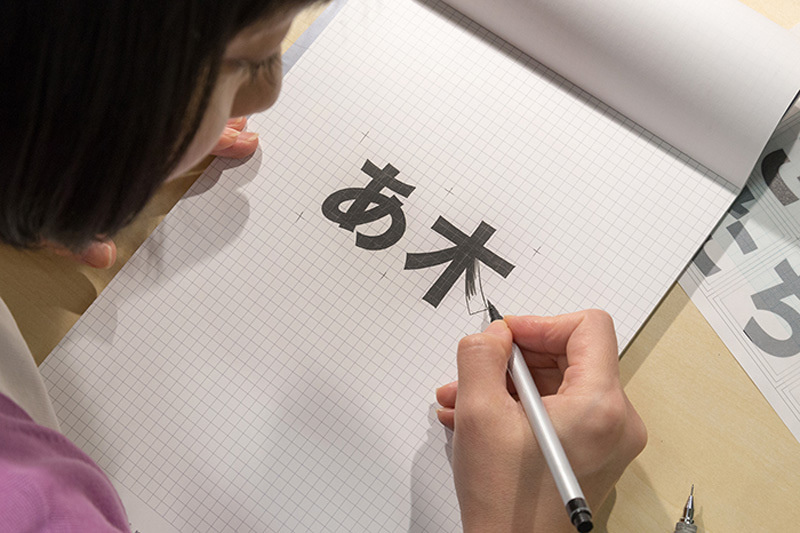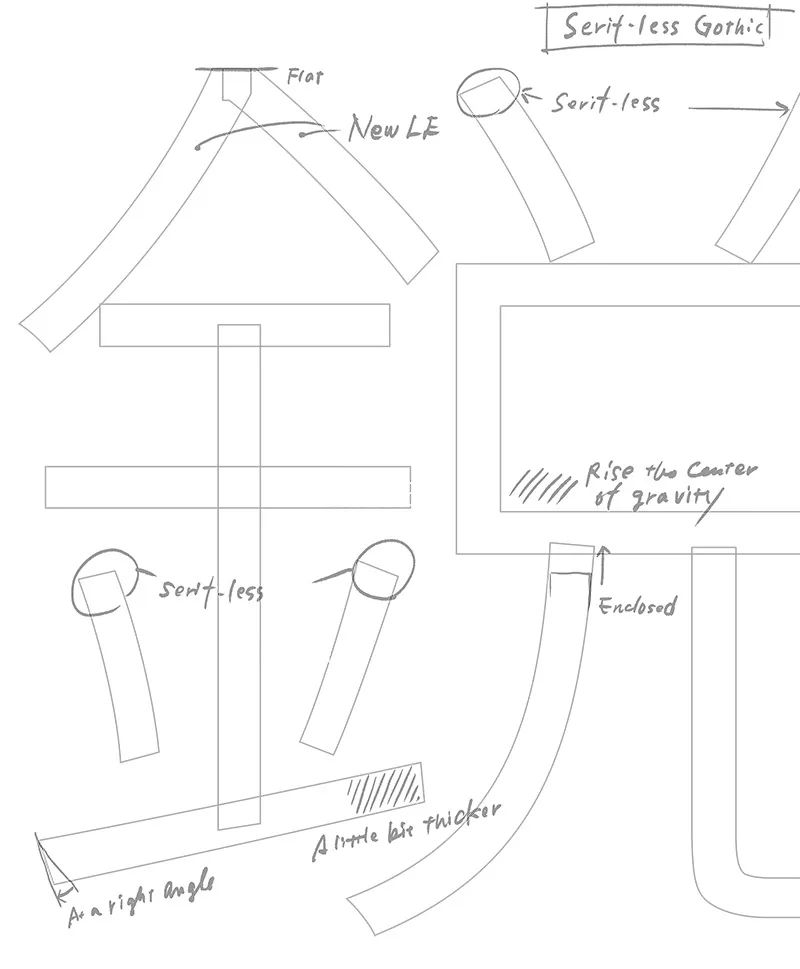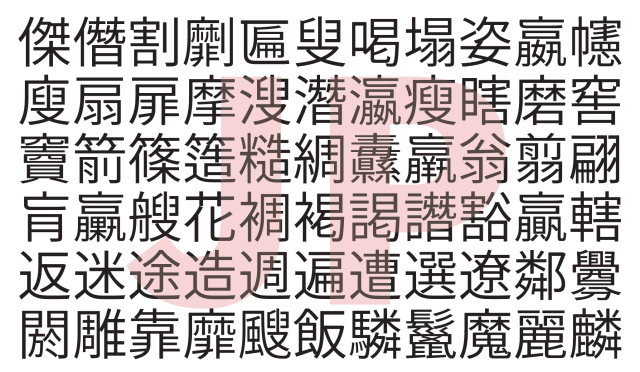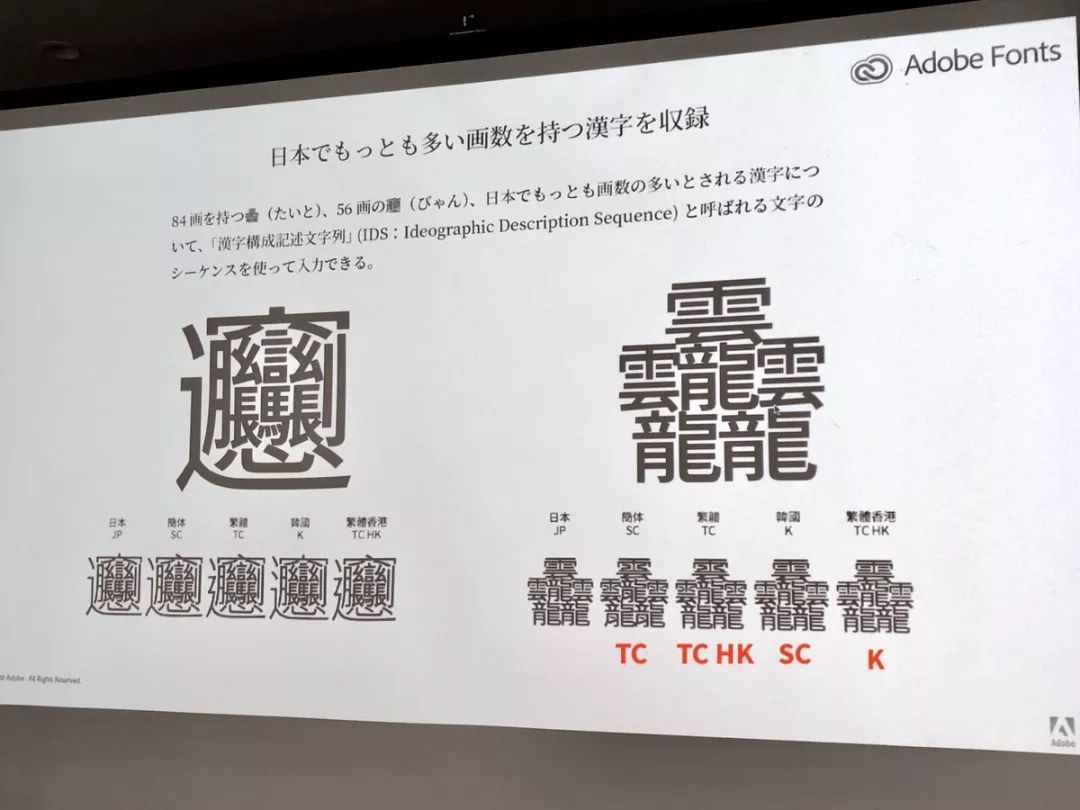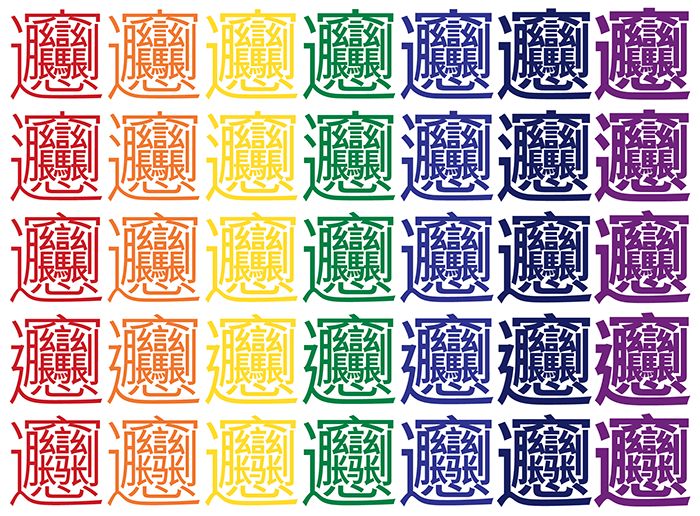
▲ 字体设计师西冢凉子(Ryoko Nishizuka)正在设计思源黑体的一些字符
思源黑体(Source Han Sans)“思源”一词来自于成语“饮水思源”是Adobe与Google所领导开发的开源字体家族。思源黑体的开发以Adobe的字体设计师西冢凉子为中心,西文及数字采自Source Sans Pro字体,汉字部分则分别以各语种为基础,由不同设计公司制作——日文为Iwata、中文为常州华文、韩文为Sandoll等,其字形皆依循各国国家标准。
2014年7月16日首次发布该字体,支持繁体中文、简体中文、日文及韩文,并且各有7种字体粗细,为当时涵盖字符数量最多的字体,44,666个字符分属于65,535个字形中,此为OpenType字体技术的极限。
11月19日,思源黑体2.000版本发布,最大的亮点就是增加了港版。
在2.000之前的版本只支持繁体中文、简体中文、日文及韩文的汉字写法,而其中繁体中文初始版本,命名为“TWHK”,可是这版本的汉字写法只据国字标准字体为准,不支持香港教育标准,也不支持传统印刷体字形。
现在,2.000这个版本加入了香港汉字写法,将台湾及香港的繁体中文字体分开。此外也加入了约1,750个新字形以及加入了将在中日韩统一表意文字扩展区G加入Unicode的Biáng字。